品牌定制字体是什么?看完就了解
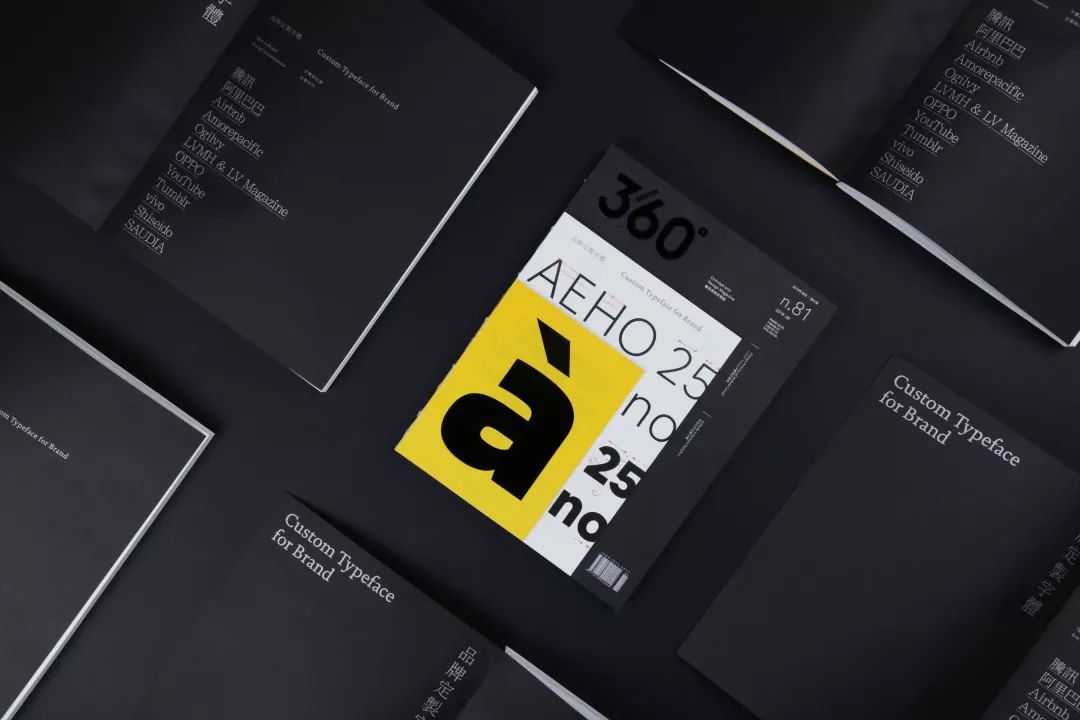
近年来,品牌字体相关的新闻层出不穷:从去年各大奢侈时尚品牌争先更新LOGO字体,到阿里巴巴、腾讯、OPPO等企业前后推出品牌字体,让品牌定制字体这一话题再次引起热议。
字体的重要性被重提,一方面,是因为在小屏幕阅读的情况下,字体成为品牌视觉形象与文本内容的双重载体,由此,字体的品牌传播价值显得日益重要而无可比拟;另一方面,随着各大品牌业务的国际化以及线上线下的多维度渗透,字体更是发挥着跨地域、跨媒介地协调统一品牌形象的关键作用。
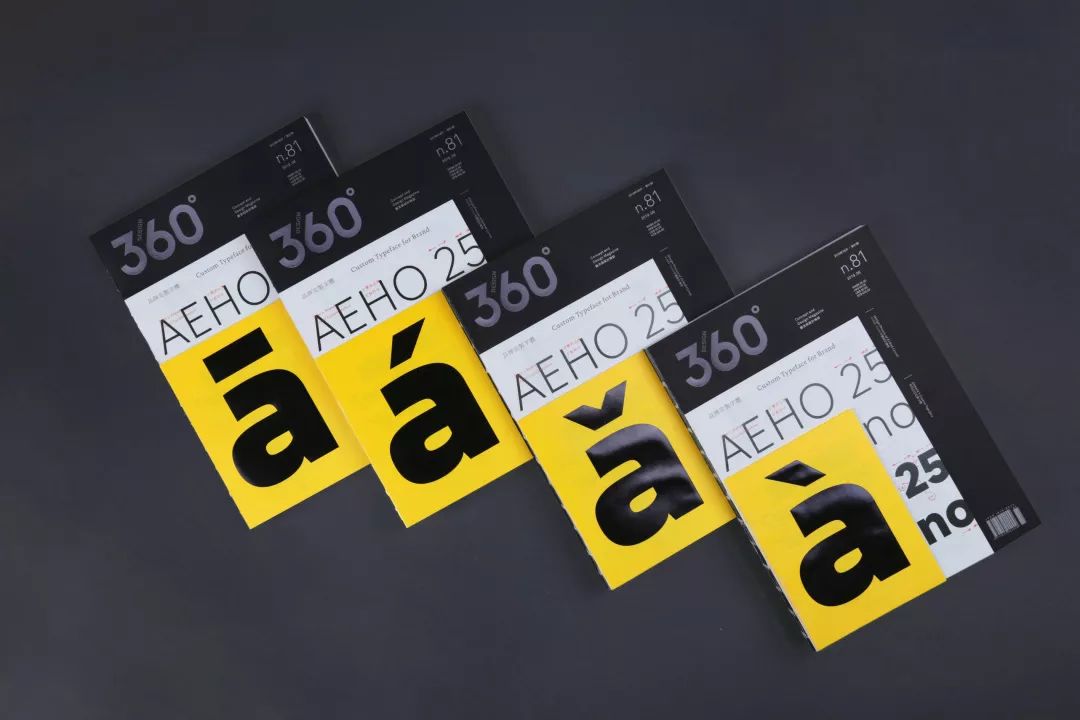
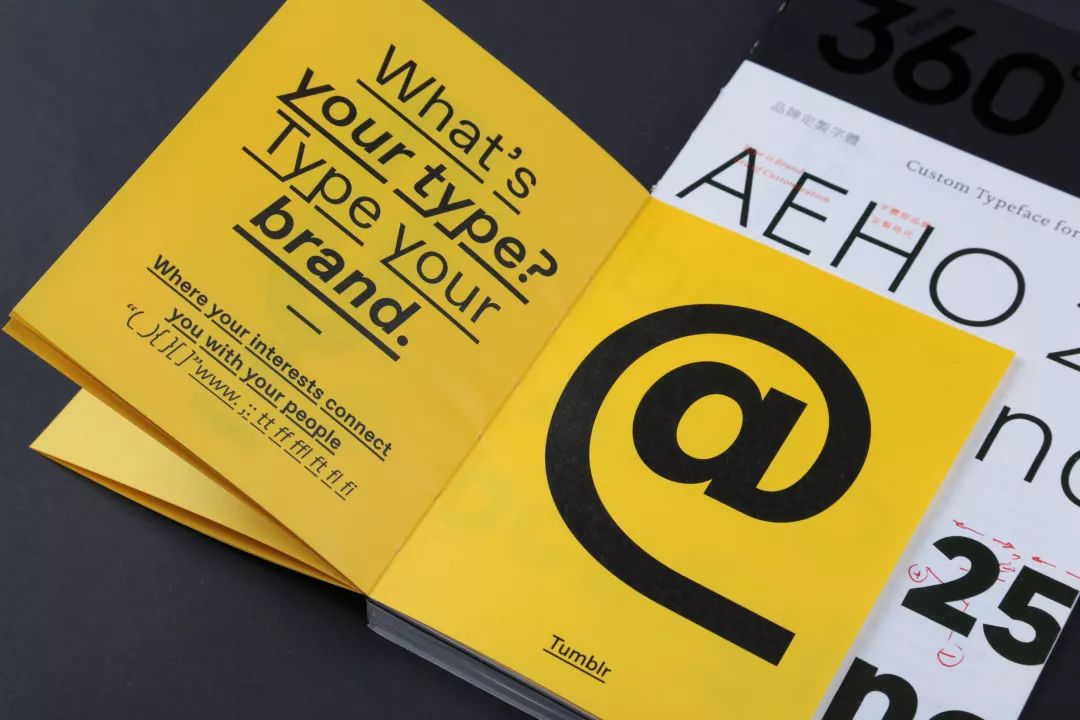
本期Design360°以“品牌定制字体”为专题,集合12款跨互联网、零售、广告、航空等行业的品牌定制字体,探索设计师如何在一笔一画中实现品牌在“定制时代”里对识别度的高要求,同时也为受众提供流程细腻的阅读体验。本期主题最大的特点在于双向的解读:除了从字体设计师的角度出发,还邀请了企业甲方来阐述它们对字体定制的策略考虑和设计需求。从品牌到字体,再从字体到品牌,本期希望让读者能够比较完整地了解品牌定制字体项目背后的思考,并感受这些耳熟能详的品牌对每个细节的品质把控。
◇ Design360°首次推出一期4式封面
A册封面将拉丁文首字母“a”和中文拼音四声调结合
除了寓意让字体“发声”
还蕴含本期杂志对中文品牌字体设计的关注
◇ What is your type?Type your brand!
A册用7款品牌字体展示同一句话
并配上各品牌的口号及标志性符号
直观感受定制字体所带来的不一样的品牌性格
◇ 腾讯 - 腾讯体
腾讯 × 蒙纳
◇ 阿里巴巴 - Alibaba Sans及阿里巴巴普惠体
Alibaba Design × 蒙纳 × 汉仪字库
◇ Airbnb - Airbnb Cereal
Airbnb × Dalton Maag
◇ 爱茉莉太平洋 - 阿丽达黑体
爱茉莉太平洋 × 汉仪字库
◇ 奥美 - Ogilvy Serif and Sans
COLLINS × MCKL
◇ LVMH & LV Magazine
LVMH Air、LV Clémence、LV Loys Sans Condensed
Production Type
◇ OPPO - OPPO Sans
Pentagram × 汉仪字库
◇ YouTube - YouTube Sans
Saffron Brand Consultants
◇ Tumblr - Favorit Tumblr
Dinamo
◇ vivo - vivo Type
方正字库
◇ 资生堂 - 资生堂书体
资生堂
◇ SAUDIA 沙特阿拉伯航空 - SAUDIA定制字体
Fontsmith
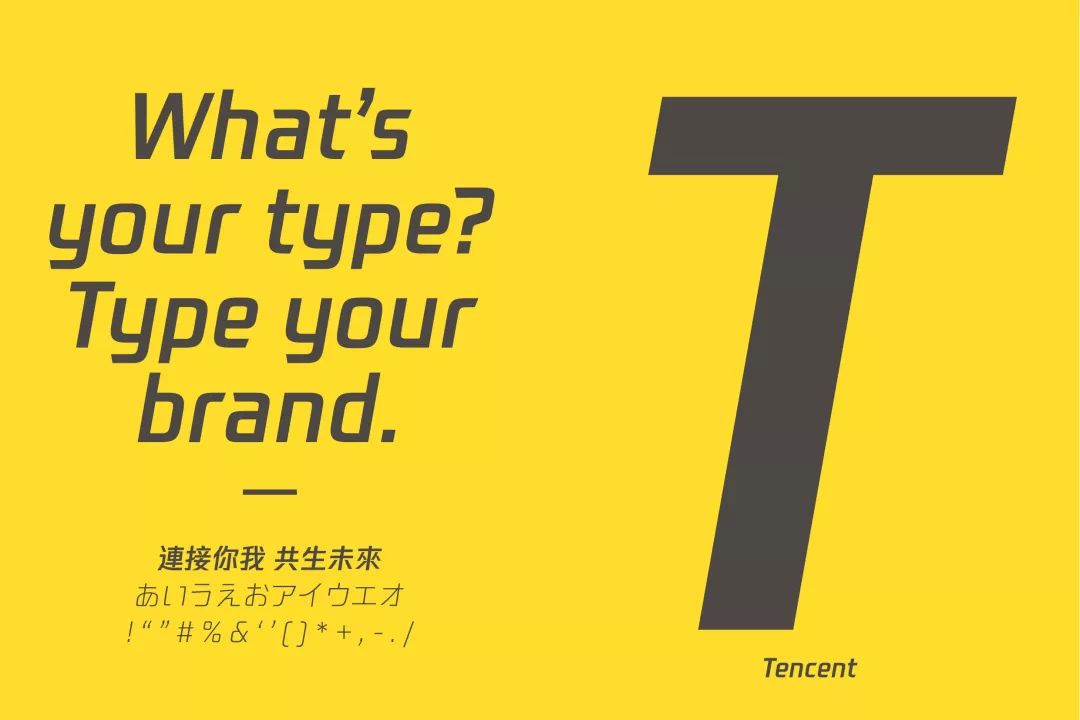
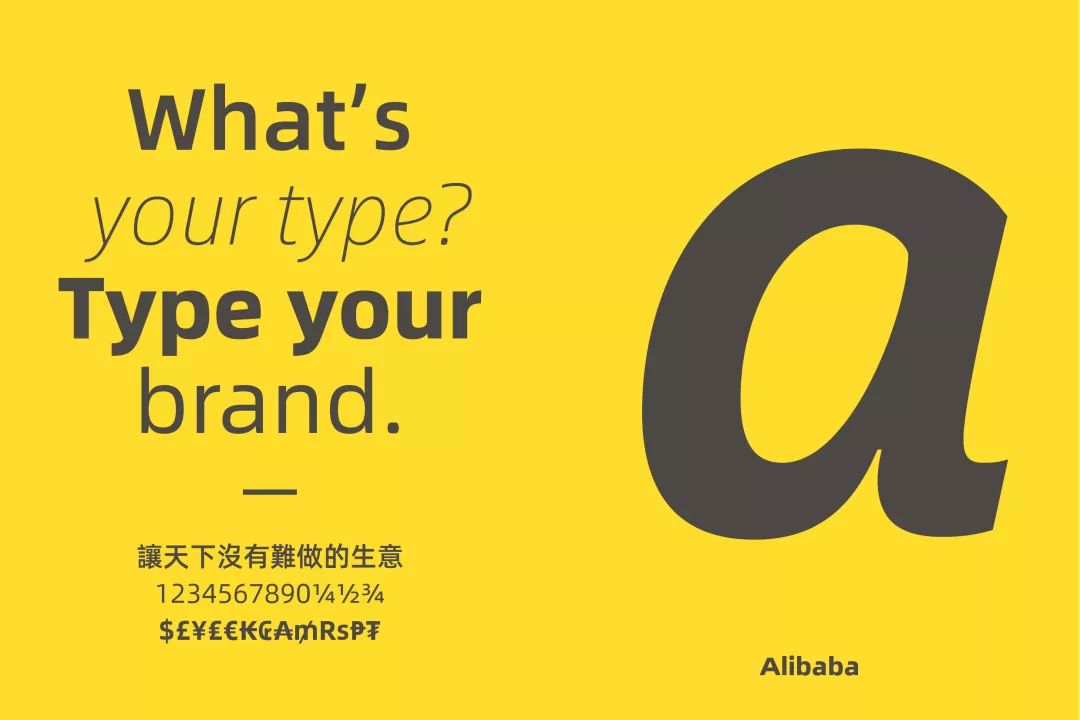
腾讯体
腾讯 × 蒙纳
腾讯体是基于腾讯新标识中的“腾讯”二字而设计的斜体字库,其最初设想的场景就是标题字和标识标准字。对于拥有丰富多样的产品与服务的大型互联网企业来说,腾讯期望其定制字体既满足子品牌的定位和个性需求,又能注入母品牌的能量进行背书。
阿里巴巴定制字体
Alibaba Design × 蒙纳 × 汉仪字库
由Alibaba Sans和阿里巴巴惠普体两部分组成,利用符合字形式和字重细节差异化实现对不同使用场景的适配。作为有着庞大企业生态系统的企业平台,通过推出定制字体,阿里巴巴旨在强化品牌视觉整体性与一致性,同时期望解决平台商家字体侵权案例频发的问题,从而创造赋能整个生态。
Airbnb Cereal
Airbnb × Dalton Maag
Airbnb Cereal的6款字重,让爱彼迎用户在不同媒介上都能够体验到它一致的调性和易读性。它满足了企业与日俱增的个性、功能及规模需求,在让品牌脱颖而出的同时兼顾了线上和线下的应用。
Ogilvy Serif and Sans
COLLINS × MCKL
世界上最大的广告代理商之一奥美在80多个国家建立了132个分支机构。在奥美宣布重组后,推出了全新的视觉识别系统并定制了两款字体以重新梳理品牌架构。Ogilvy Serif and Sans改编自创始人David Ogilvy最喜欢的字体Baskerville,既与其60年传奇历史保有连接,又为奥美注入现代气息。
阿丽达黑体
爱茉莉太平洋 × 汉仪字库
爱茉莉太平洋集团是总部位于韩国首尔的全球性化妆品和保健品企业,早在2005年便推出韩文企业字体。其初衷出自爱茉莉太平洋认为企业应该对文化有所贡献的理念,运用韩文设计特征,搭配中文字体“留白”的特点,提取隶书精髓,打造了“健康的东亚之美”的印象。
LVMH & LV Magazine
Production Type
作为全球最大的奢侈品集团之一,LVMH追求的是一款可以强化品牌、确立美学视野、以及最重要的是体现知性深度的字体。其定制字体采用了一种超过五个世纪以来被广泛接受的经典设计方案,体现出“未来经典”的品牌理念。
OPPO Sans
Pentagram × 汉仪字库
OPPO追求品质和工艺的手机产品远销世界各地,字体成为了其品牌识别的关键工具。OPPO Sans包含拉丁文、西里尔文和中文,作为具有理性注意的无衬线字体,它被运用在产品和所有市场宣传材料中,使得OPPO在全球的高品质产品展示上更真实可信。
YouTube Sans
Saffron Brand Consultants
不断发展的新业务和不断扩大的用户群促使YouTube重新考虑其品牌策略,YouTube Sans则是作为其新视觉系统的一部分开发的,目的是更好地传达该平台及其内容的开放特质。
Favorit Tumblr
Dinamo
在Tumblr品牌识别系统全面改革的过程中,Tumblr内部设计团队一眼相中了独立研发字体Favorit,以此作为基础与字体厂牌合作定制Tumblr品牌专用的Favorit,提高了品牌的统一性,又显得前卫大胆。
vivo Type
方正字库
vivo品牌已经登陆18个国家和地区,为了加快推动全球化的品牌推广建设,vivo对其品牌标识和品牌字进行升级重塑。vivo Type应用在品牌的产品设计和宣传推广中,展现出鲜明、独特的科技属性与时尚调性。
资生堂书体
资生堂
资生堂的品牌字体资生堂书体的起源追溯到上世纪20年代,最初由第一任社长福原信三创造,之后由企业内部设计师通过手绘形式持续优化,现已发展为资生堂品牌设计的核心。在创意本部,新员工回学习绘制基础的资生堂书体,由此品牌将美感传递给一代又一代的创意人。
沙特阿拉伯航空 SAUDIA 定制字体
Fontsmith
作为连接东西方世界的大型航空公司,沙特阿拉伯航空SAUDIA不仅需要一套成熟且能满足不同功能的字体,还需要创造由拉丁语和阿拉伯语组成的、完整且连贯的字体系统,助其成为“阿拉伯世界最好”的航空公司。